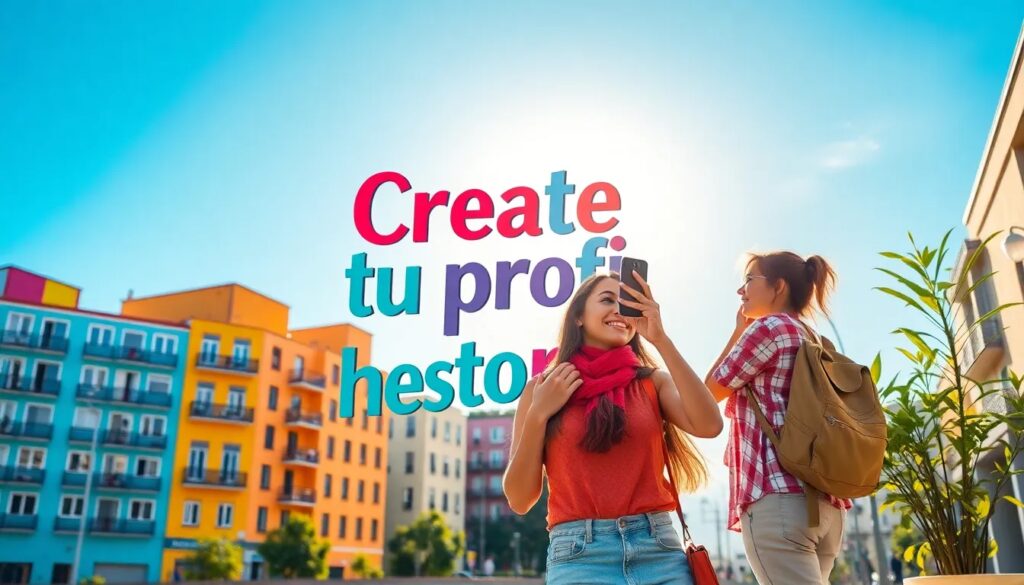
Tipografía en Instagram
La tipografía es un elemento esencial para destacar en las redes sociales, y en Instagram no es la excepción. Con el uso de diferentes estilos y fuentes, puedes hacer que tus publicaciones y biografía sean mucho más atractivas. En este artículo, exploraremos cómo puedes utilizar fuentes únicas y personalizadas para mejorar tu presencia en Instagram.
Desde cursivas elegantes hasta fuentes decorativas llamativas, el generador de fuentes para Instagram puede transformar tu texto de ordinario a extraordinario. Sigue leyendo para descubrir cómo cambiar tu tipografía y dónde encontrar las mejores opciones.
¿Qué es la tipografía en Instagram?
La tipografía en Instagram se refiere al estilo de texto que puedes utilizar en tus publicaciones y biografía. Esto incluye diferentes fuentes, tamaños, y estilos que pueden añadir un toque personal a tu perfil.
El uso creativo de la tipografía puede hacer que tu contenido resalte entre la multitud, ayudándote a captar la atención de tus seguidores. Al final, la tipografía adecuada puede influir en la percepción de tu marca o perfil.
Además, Instagram permite el uso de caracteres especiales y emojis, lo que te da aún más opciones para personalizar tu texto. Esto es especialmente útil para quienes desean hacer que sus biografías sean memorables.
¿Cómo cambiar la tipografía en Instagram?
Cambiar la tipografía en Instagram es un proceso sencillo que puedes realizar con herramientas en línea. Aquí te explicamos los pasos básicos:
- Visita un generador de fuentes: Existen múltiples generadores de texto que te permiten crear fuentes estilizadas.
- Escribe tu texto: Inserta el texto que deseas transformar en el generador.
- Selecciona el estilo: Explora las diferentes opciones de estilo que ofrece el generador y elige el que más te guste.
- Copia y pega: Una vez que hayas encontrado la tipografía perfecta, simplemente cópiala y pégala en tu biografía o publicación de Instagram.
Recuerda que algunas fuentes pueden no mostrarse correctamente en todos los dispositivos, así que es recomendable hacer pruebas antes de utilizarlas ampliamente.
¿Cómo obtener texto elegante en Instagram?
Para obtener texto elegante en Instagram, puedes utilizar varias técnicas. Una de las más efectivas es el uso de fuentes cursivas o decorativas que añaden un toque distintivo a tus publicaciones.
Además de usar generadores de fuentes, puedes combinar tus textos elegantes con emojis para darle un aspecto más vibrante. Esto no solo atraerá más atención, sino que también puede expresar mejor tus emociones o la temática de la publicación.
Otra opción es utilizar aplicaciones de diseño que te permiten crear imágenes con texto estilizado. Estas aplicaciones ofrecen una variedad de herramientas y plantillas que pueden hacer que tu contenido se vea aún más profesional.
¿Cómo hacer la fuente de escritura en Instagram?
Hacer una fuente de escritura en Instagram es más fácil de lo que parece. Con un generador de texto adecuado, puedes transformar rápidamente tu texto en diferentes estilos. Simplemente sigue estos pasos:
- Accede a un generador de fuentes en línea.
- Introduce el texto que quieres cambiar.
- Prueba varios estilos hasta encontrar el que más te guste.
- Copiar y pegar el texto estilizado en Instagram.
Recuerda que la coherencia en el estilo es clave. Si decides usar una fuente elegancia, asegúrate de que se alinee con tu mensaje general y la estética de tu perfil.
¿Dónde encontrar fuentes de letras para Instagram?
Existen numerosas plataformas en línea donde puedes encontrar fuentes de letras para Instagram. Estos generadores son especialmente útiles porque te permiten ver cómo se verá el texto antes de utilizarlo. Algunos de los más populares son:
- Font Generator: Una herramienta sencilla que ofrece múltiples estilos de texto.
- Cool Symbol: Permite crear textos decorativos y combinar con símbolos.
- Lingojam: Esta plataforma te permite ver una vista previa de cómo quedará tu texto en diferentes estilos.
Además, muchas aplicaciones de diseño gráfico como Canva o Adobe Spark también ofrecen opciones para crear texto estilizado, lo que puede ser muy útil para tus publicaciones.
¿Qué tipos de fuentes se pueden usar en Instagram?
En Instagram, puedes utilizar varios tipos de fuentes, incluyendo:
- Fuentes cursivas: Perfectas para dar un toque elegante a tus publicaciones.
- Fuentes decorativas: Ideales para destacar citas o mensajes importantes.
- Fuentes de tipo máquina de escribir: Aportan un estilo retro y nostálgico a tus textos.
La clave está en elegir una fuente que se alinee con la imagen de tu marca o tu estilo personal. No tengas miedo de experimentar hasta encontrar la que mejor te represente.
¿Cómo personalizar tu perfil de Instagram con fuentes?
Personalizar tu perfil de Instagram con fuentes únicas puede hacer una gran diferencia en la forma en que te perciben tus seguidores. Aquí van algunos consejos:
Utiliza fuentes estilizadas en tu biografía para destacar tu personalidad. Combina también con emojis que reflejen tus intereses o tu estilo de vida, creando un perfil visualmente atractivo.
Otra técnica es variar la tipografía en tus publicaciones. Por ejemplo, puedes usar una fuente para las citas y otra para tus descripciones, lo que ayuda a que tu perfil se vea más dinámico y menos monótono.
No olvides que la coherencia es fundamental. Mantén un estilo que se ajuste a tu temática general y asegúrate de que todas las fuentes usadas sean legibles en dispositivos móviles.
Preguntas relacionadas sobre tipografía en Instagram
¿Qué es Instagram typography?
La Instagram typography se refiere a las diferentes maneras en que puedes presentar texto en la plataforma, usando estilos y fuentes variadas. Esto incluye el uso de caracteres especiales, emojis y tipografías creativas que le dan un toque único a tu contenido.
Además, gracias al estándar Unicode, puedes utilizar una amplia gama de caracteres y símbolos que enriquecen aún más tus publicaciones. Esto permite una representación más atractiva de tu mensaje, haciendo que destaque en el feed de tus seguidores.
¿Cómo cambiar la typography on Instagram?
Cambiar la typography on Instagram es un proceso rápido. Simplemente utiliza un generador de fuentes, introduce tu texto, selecciona el estilo deseado y copia el resultado. Luego, pégalo en tu biografía o en tus publicaciones.
Es recomendable experimentar con diferentes estilos para ver cuál se adapta mejor a tu contenido y a tu audiencia, garantizando así una mejor conexión con tus seguidores.
How to get fancy text on Instagram?
Para get fancy text on Instagram, puedes emplear generadores de texto que ofrecen estilos únicos como cursivas o decorativas. Esto te permitirá agregar un toque especial a tus publicaciones.
Adicionalmente, combinar tu texto elegante con emojis puede hacer que tu mensaje sea aún más atractivo y divertido. Prueba diferentes combinaciones para encontrar la mezcla perfecta.
How to do the typing font on Instagram?
Para hacer la typing font on Instagram, lo más efectivo es utilizar un generador de fuentes que imite ese estilo específico. Simplemente escribe tu texto y selecciona la opción que más se asemeje a un estilo de máquina de escribir.
No olvides que la legibilidad es clave, así que asegúrate de que el estilo que elijas sea claro y fácil de leer, independientemente del dispositivo en el que se visualice.